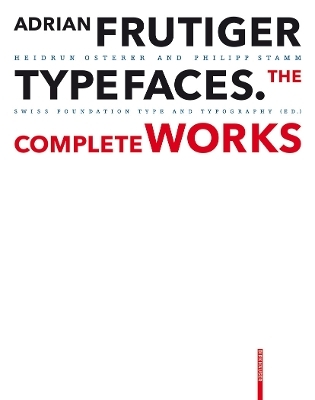
Adrian Frutiger – Typefaces
The Complete Works
Das internationale Schriftschaffen nach 1950 wurde maßgeblich geprägt vom Schweizer Adrian Frutiger. Sein Schriftprogramm Univers und die zum ISO-Standard erklärte, maschinenlesbare Schrift OCR-B sind ebenso Meilensteine wie die zur Frutiger weiterentwickelte Schrift der Pariser Flughäfen – ein Qualitätsstandard für Signalisationsschriften. Mit den Corporate Types prägte er Firmenauftritte wie den der japanischen Kosmetiklinie Shiseido. Insgesamt entstanden rund 50 Schriften, darunter Ondine, Méridien, Avenir undVectora.Auf Gesprächen mit Frutiger basierend sowie auf umfangreichen Recherchen in Frankreich, England, Deutschland und der Schweiz, zeichnet die Publikation den gestalterischen Werdegang des Schriftkünstlers exakt nach. Es werden alle Schriften – vom Entwurf bis zur Vermarktung – abgebildet sowie mit Bezug zu Technik und zu artverwandten Schriften analysiert. Bisher unveröffentlichte, nicht realisierte Schriften sowie über 100 Logos vervollständigen das Bild. Mit dieser zweiten Auflage, einer korrigierten und durch einen Index erweiterten Studienausgabe, lässt sich Frutigers Werk noch besser erschliessen.
Introduction, School days and education, Fonts: Président, Phoebus, Element-Grotesk, Delta, Federduktus, Ondine, Méridien.- Lumitype-Schriften, Univers, Egyptienne F, Opéra, Apollo, OCR-B, Serifa, Concorde, New Devanagari, Iridium, Frutiger.- Glypha, Icone, Breughel, Versailles, LT Centennial, Avenir, Westside, Herculanum, LT Didot, Vectora, Shisheido, Pompeijana.- Rusticana, Neon, Frutiger Stones/Symbols, Capitalis/Symbolica, Nami/Tectum etc. Technical Inversions: Handsatz Blei.- Fotosatz Photon, Einzelbuchstabenguss, Zeilenguss Sofratype, Tech. OCR, Schreibsatz IBM, Letraset, Tech. CRT, Laser.- Fonts, Postscript, etc. Chronology, Bibliography.